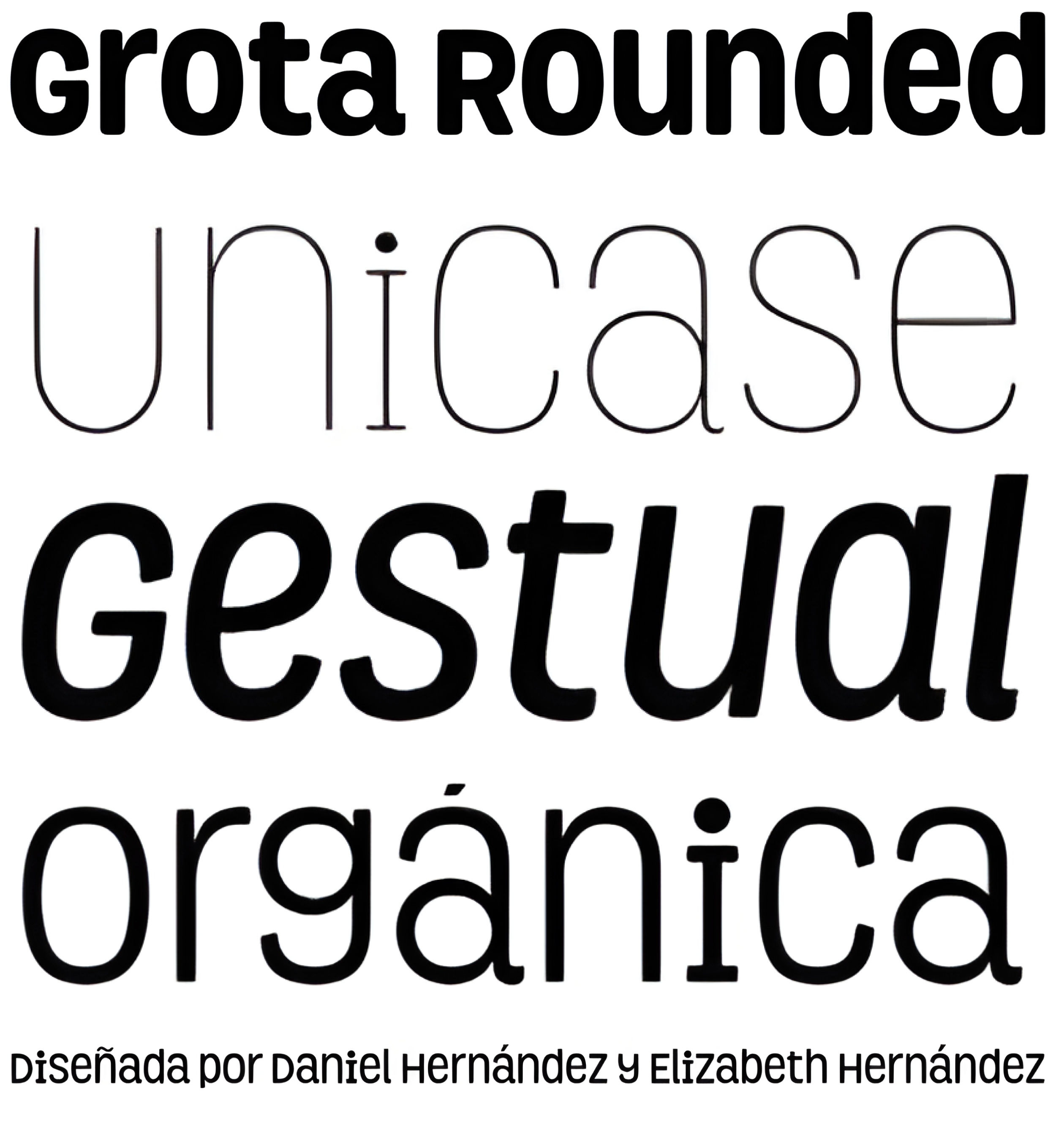
Grota Rounded
| Año | 2013 |
| Créditos | Daniel Hernández, Elizabeth Hernández |
| Descripción | Grota Rounded es una fuente muy expresiva, tiene un carácter gestual inspirado en el hand lettering . Grota Rounded es grotesca, unicase y excepcional. Tiene seis pesos que van del fino al negro con sus cursivas. Es ideal para logotipos, marcas, revistas, titulares, libros, etc. |
| Familia(s) | Grota Rounded |
| Estilos | 12 |
| Set | Especializado |